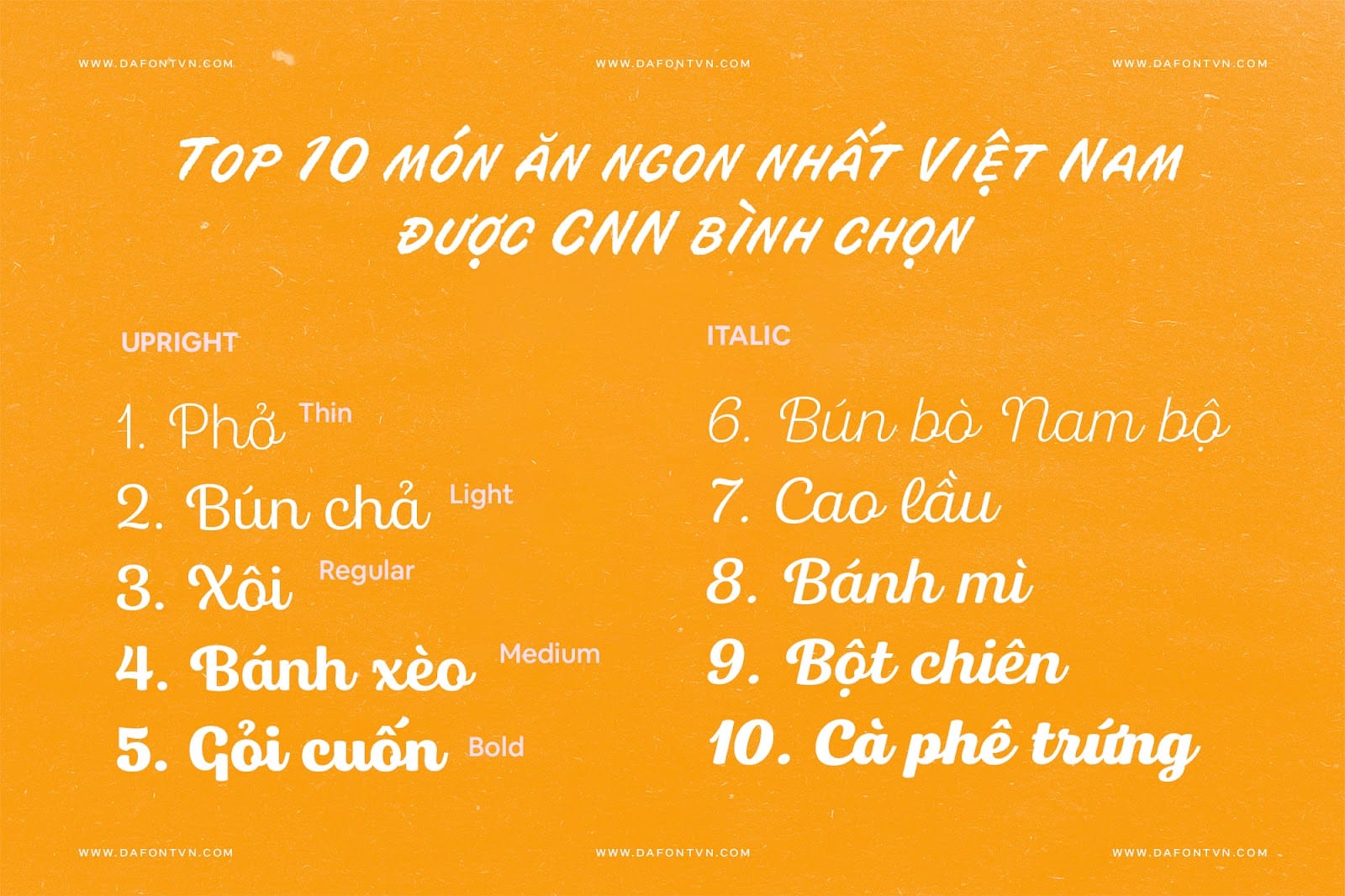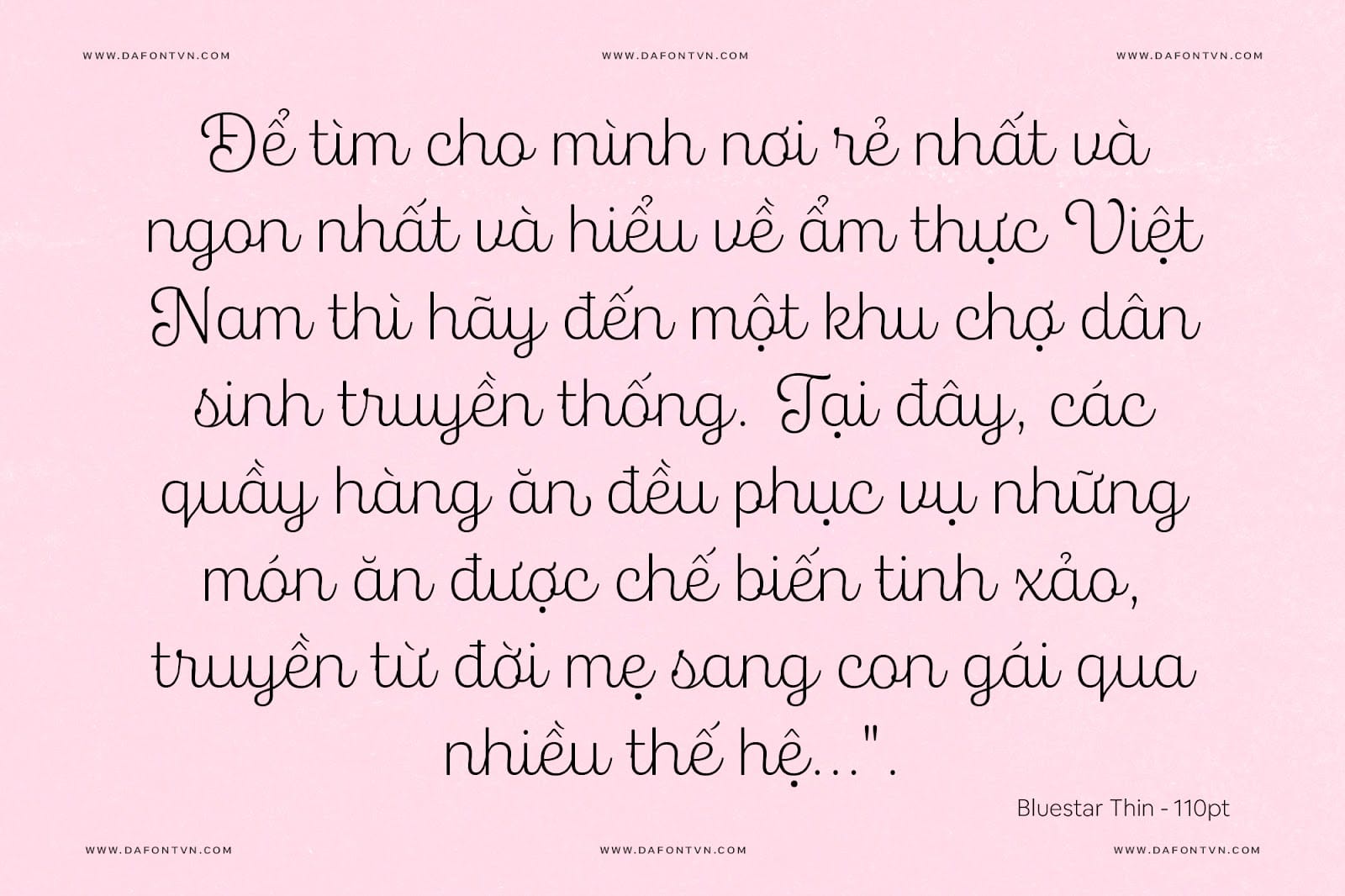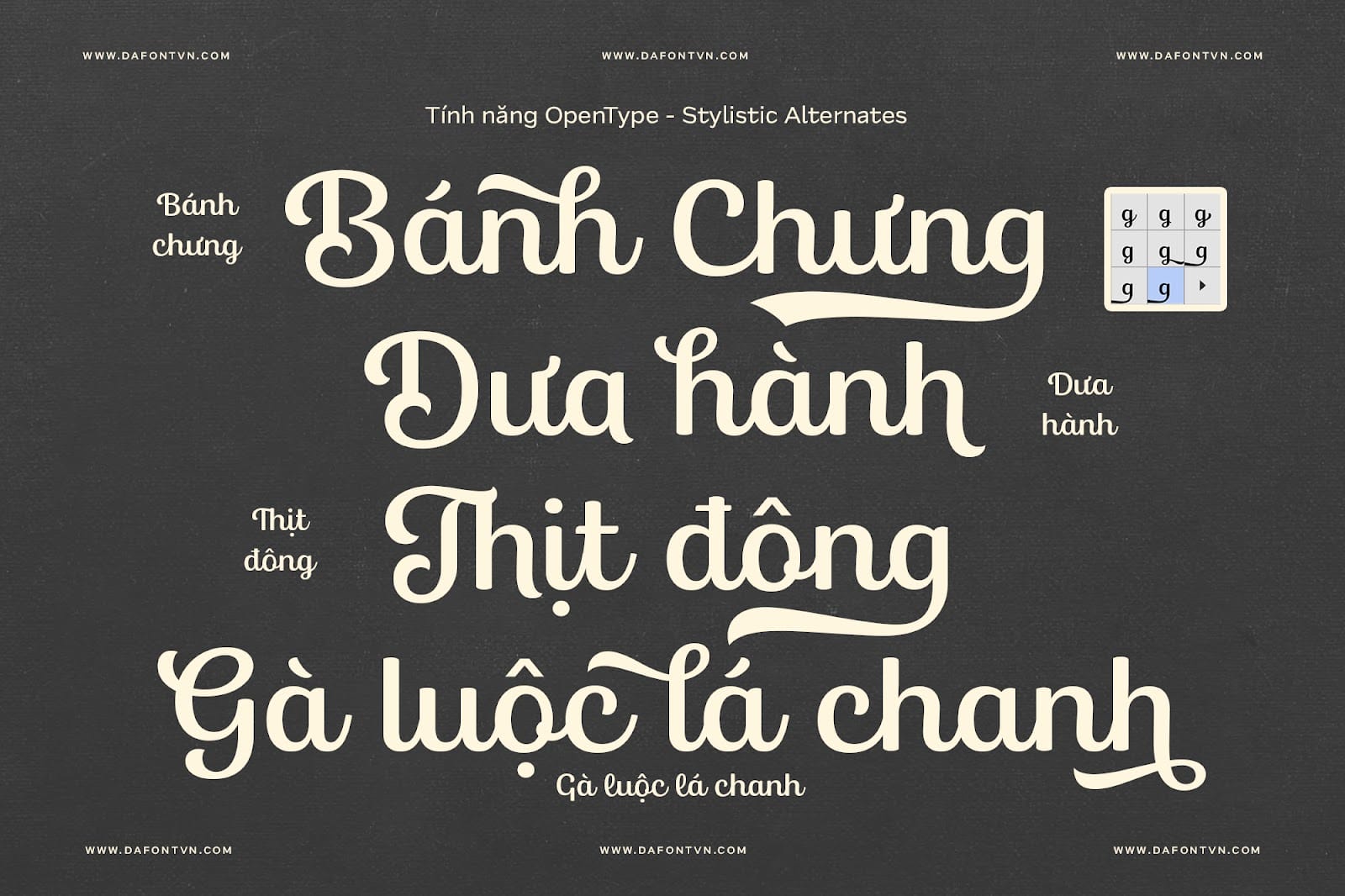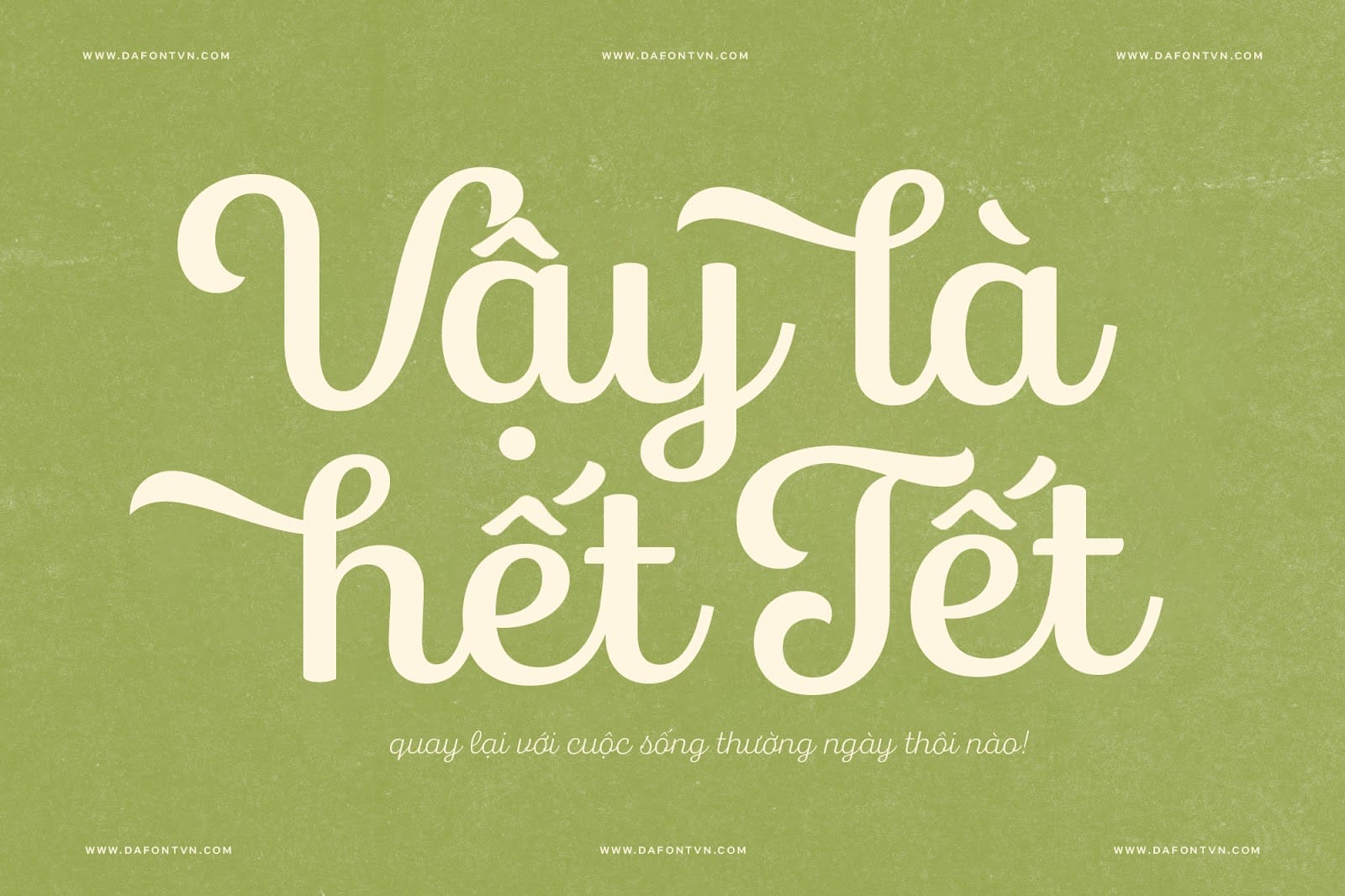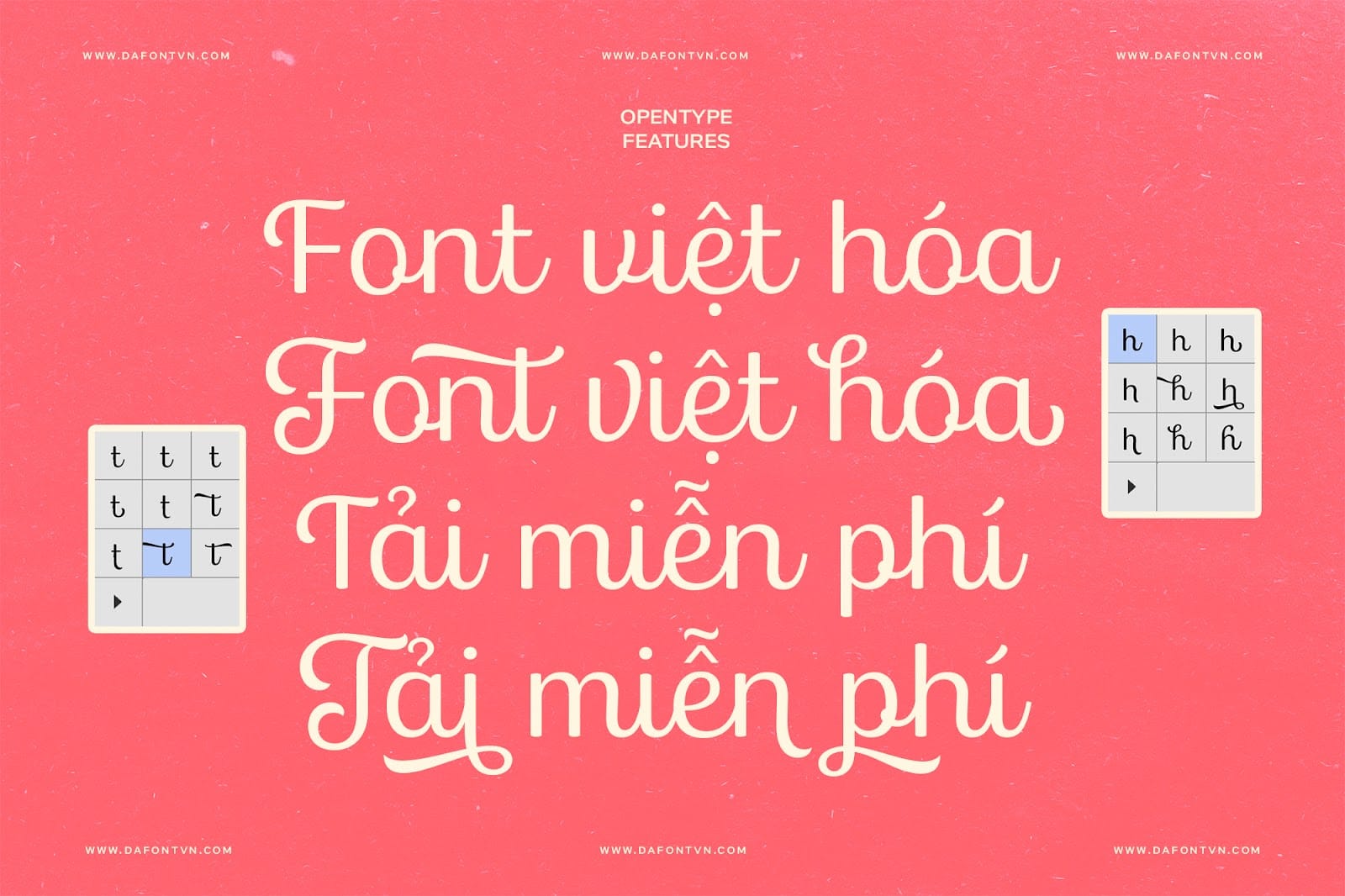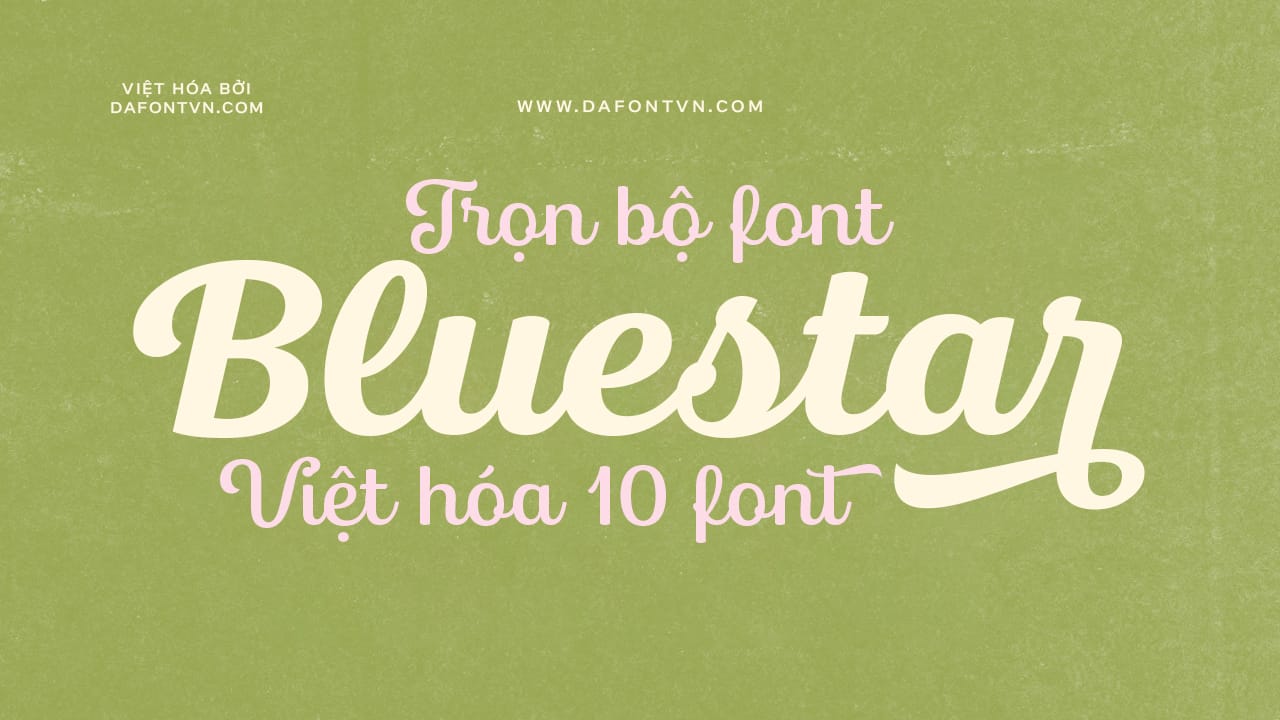
Bluestar là một kiểu chữ viết tay tròn với nét hiện đại. Các nét chữ ở đầu được thiết kế tròn và độ tương phản ấn tượng (độ tương phản là sự khác biệt giữa phần dày và phần mỏng của nét chữ và tạo ra góc nhấn trong thiết kế kiểu chữ). Tổng cộng có 10 kiểu chữ (5 kiểu đứng và 5 kiểu nghiêng).
Bluestar có 2 bộ chữ cái in hoa, một là kiểu basic và một kiểu tinh tế hơn (Stylistic Set 1) lớn hơn và phong cách hơn. Ngoài ra, Bluestar cũng có rất nhiều biến thể cho các phần tử như
ascender
(là một phần của chữ cái nằm trên dòng trung bình giống như chữ cái “b” hoặc “d),
descender
(là một đoạn kéo dài bên dưới đường cơ sở như trong “q” hoặc “g),
swash
(là những kí tăng thêm tính trang trí, với phần chân hoặc đầu được mở rộng thêm bằng các nét uốn lượn) để mang lại nhiều khả năng kết hợp và tạo ra một số thiết kế độc đáo hơn.
Bộ font được việt hóa đầy đủ, kerning, chỉnh sửa và tối ưu. Bạn có thể sử dụng bộ font này cho rất nhiều các thiết kế khác nhau hoặc cần đến một kiểu font viết tay đẹp.